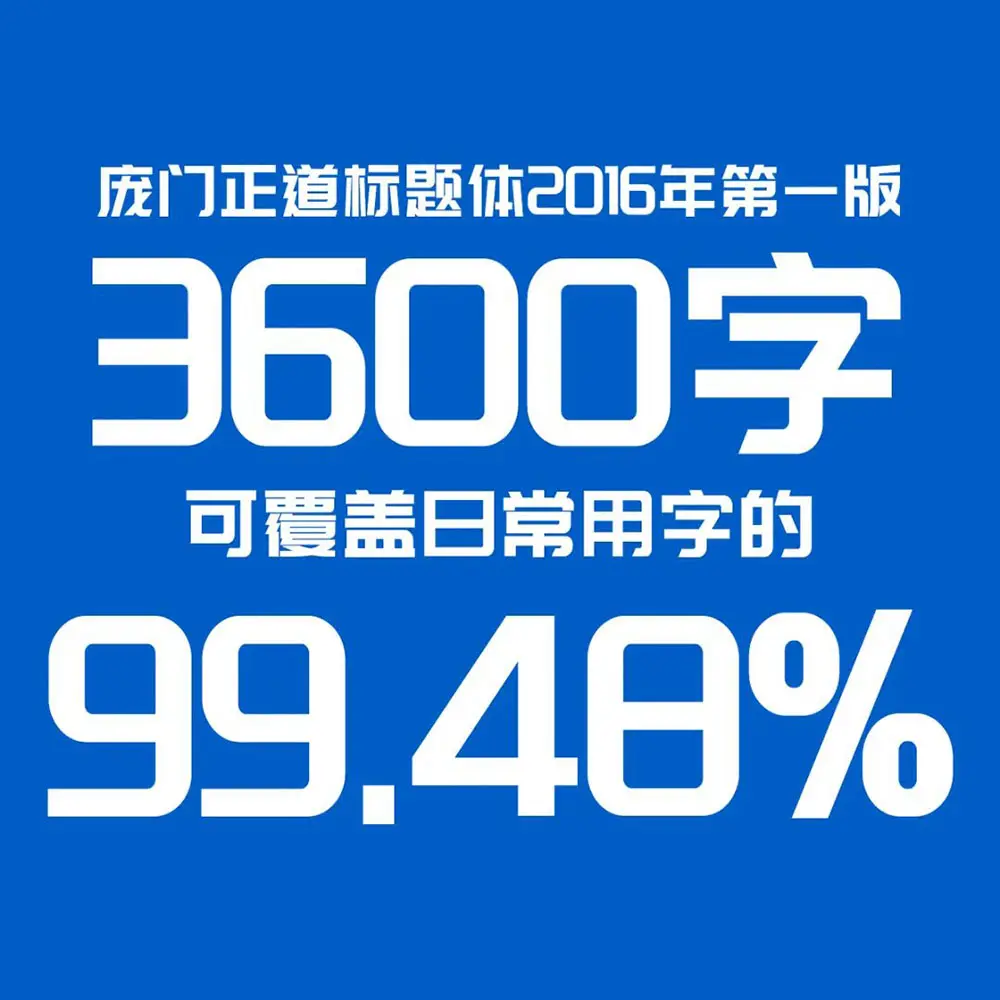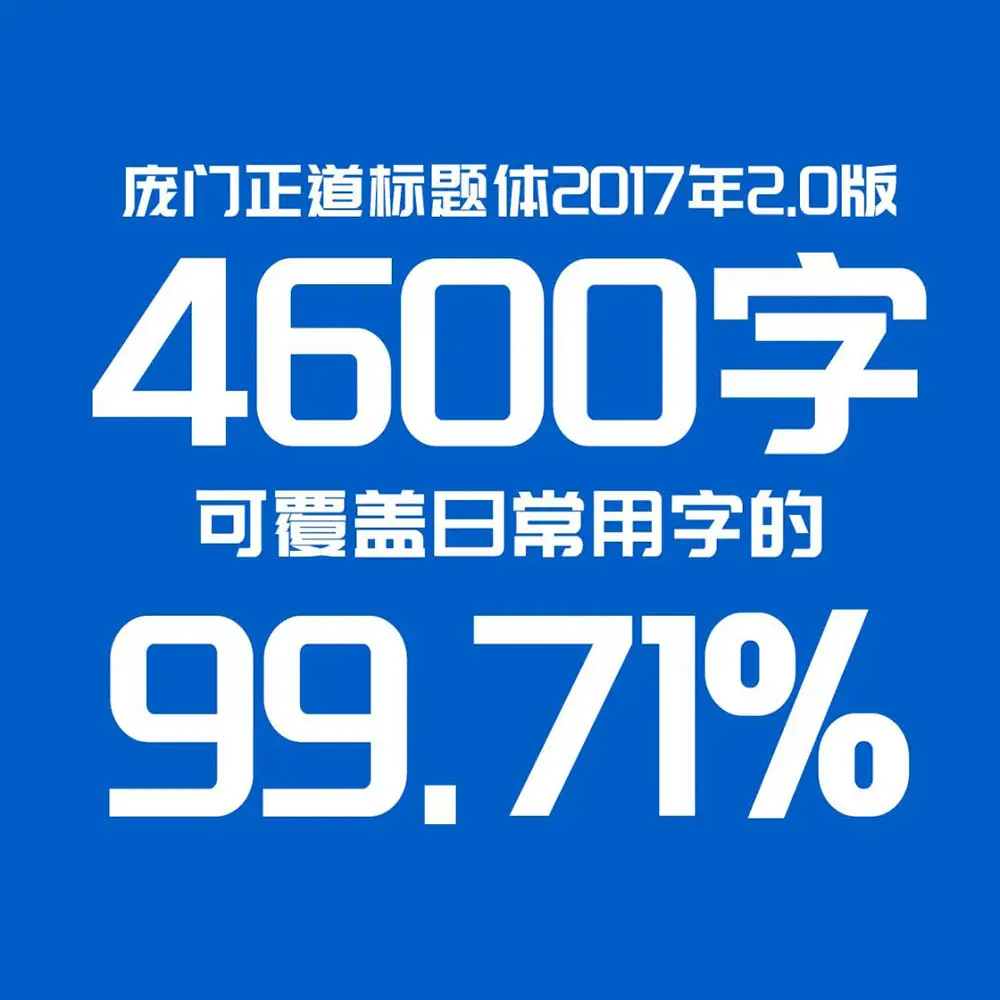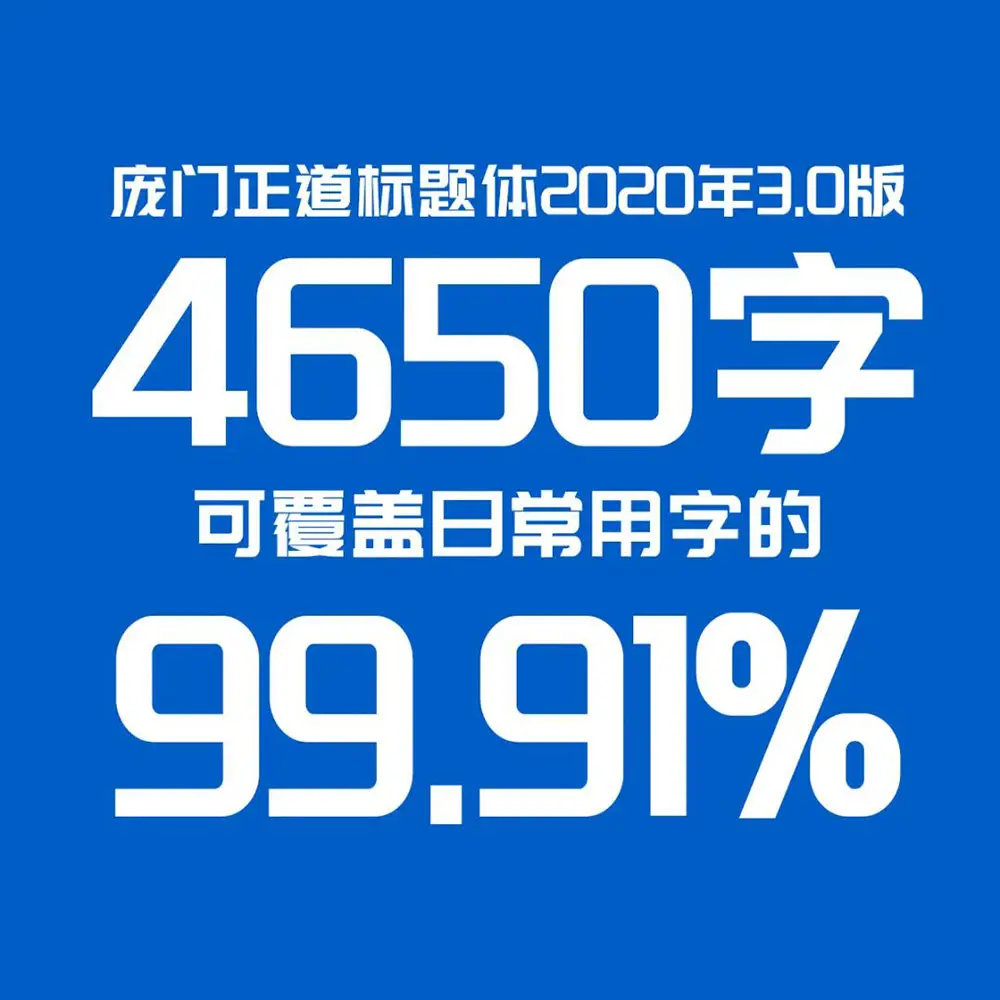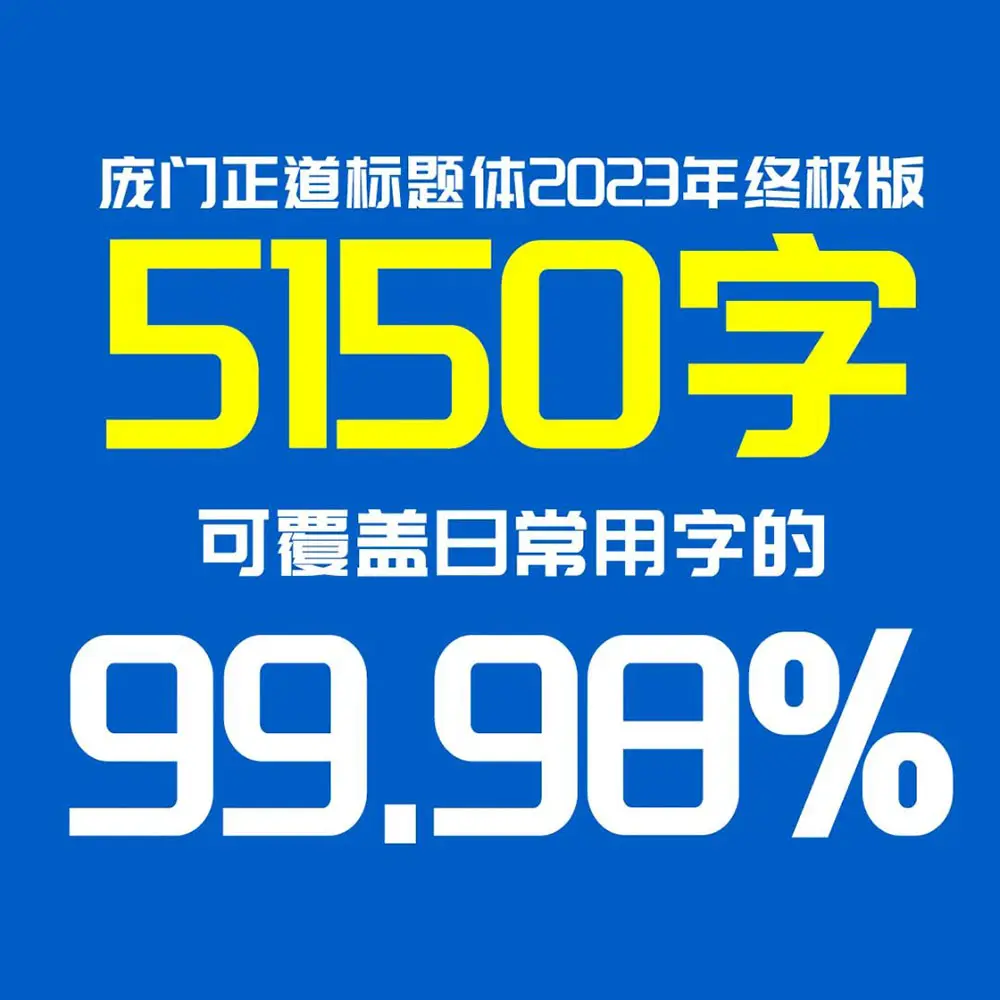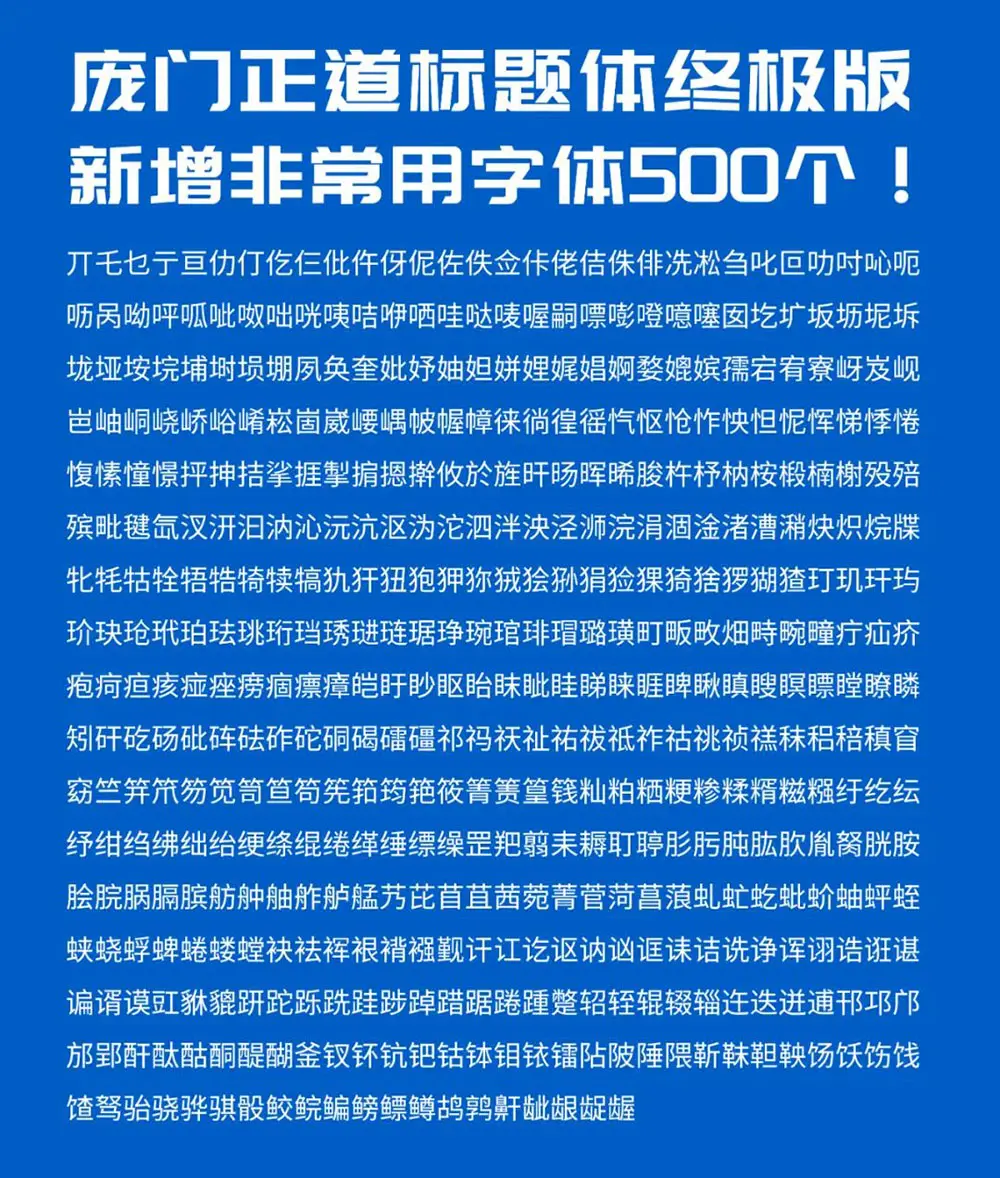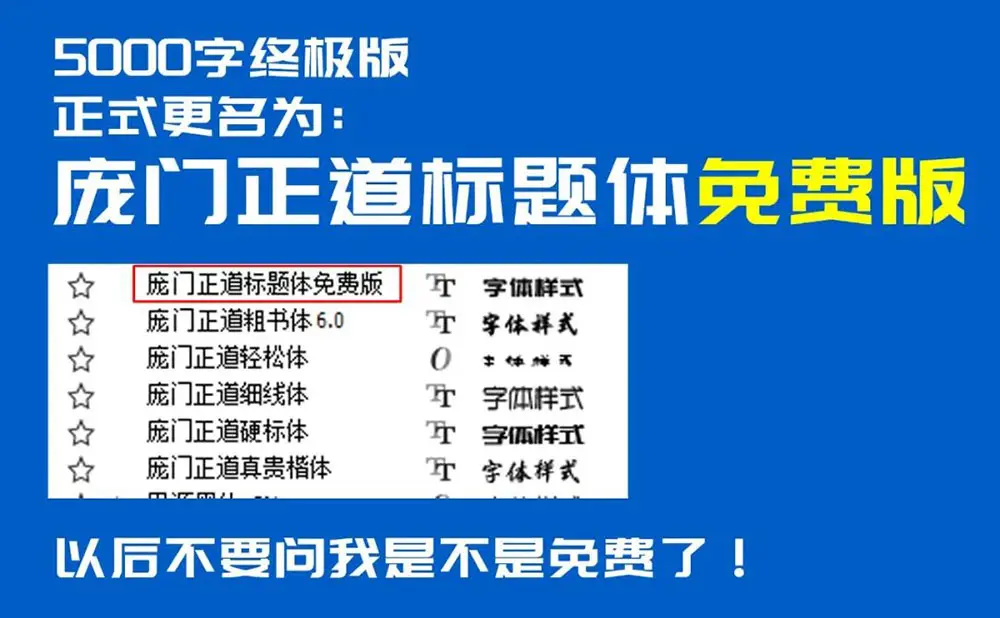
hi 下載了《龐門正道標題體》的你,首先恭喜你很有眼光。這款字體於2016年由《龐門正道》設計公眾號以及13位字體設計師耗資超過10萬元聯合研發。
2017年出了2.0版本,新增了1500箇中文字。
2020年出了3.0版本,新增了179個字符。
2023年出了終極版,新增了500字,最終中文字是5150個!